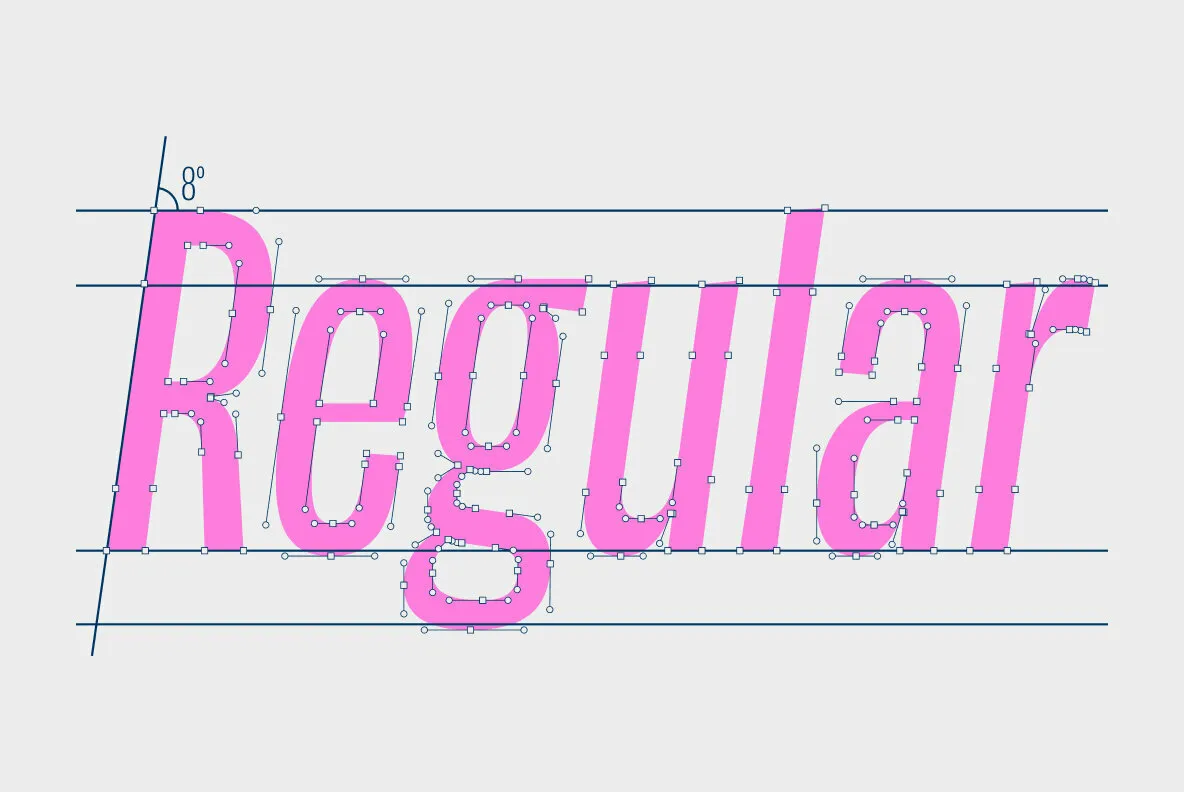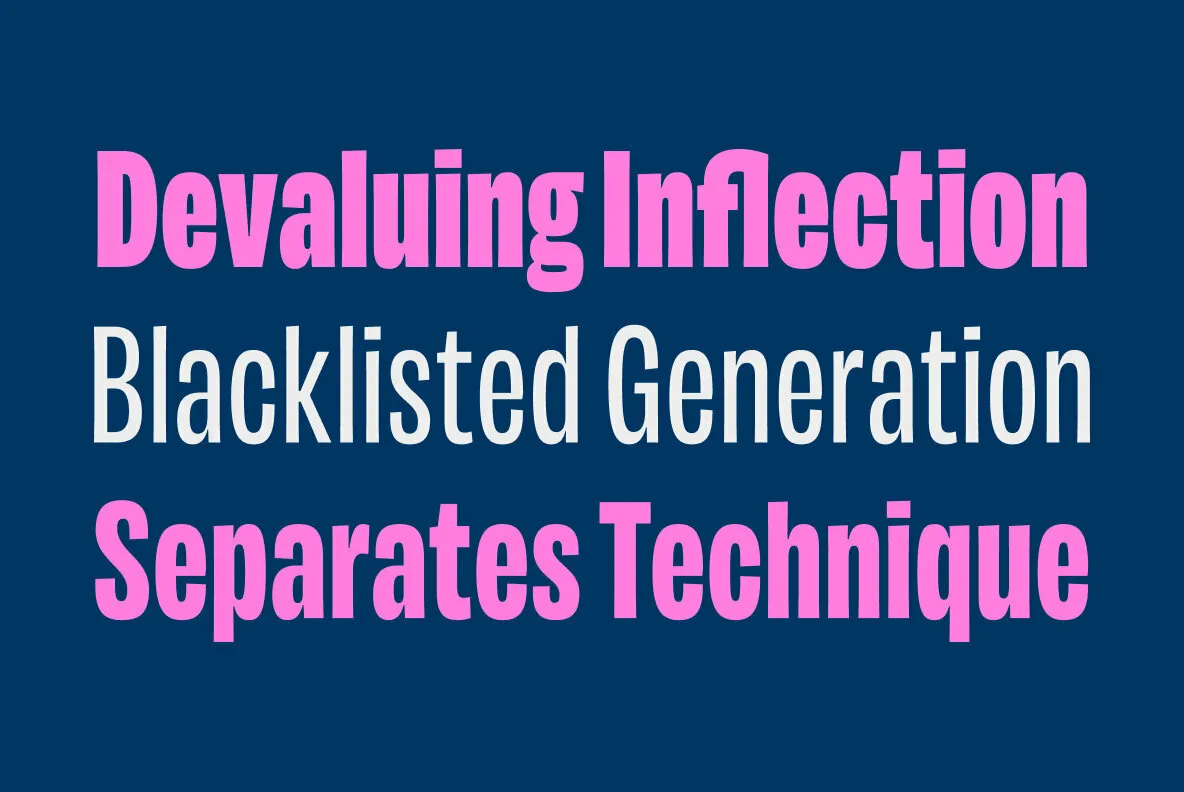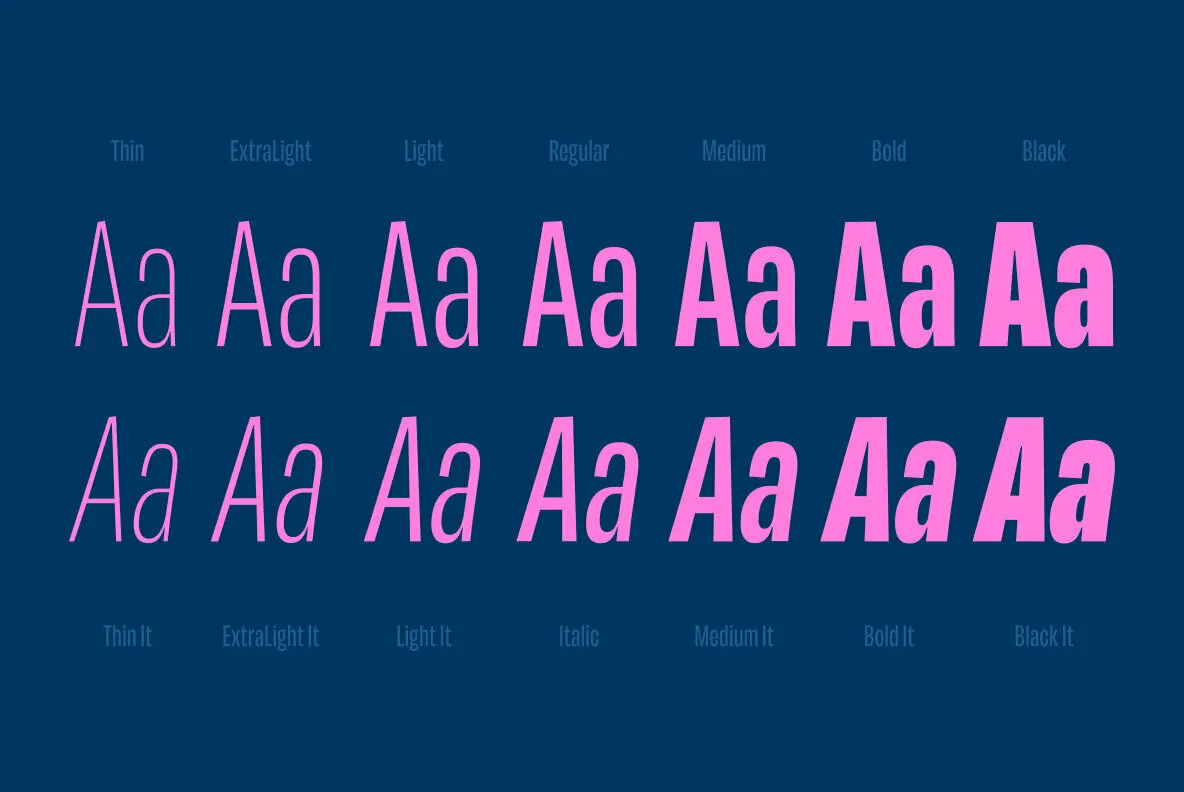
Maleo Font Family
Description de Maleo Font Family
Maleo est un sans d’affichage contemporain aux racines grotesques, s’inspirant de polices de caractères telles que Franklin Gothic et Alternate Gothic de Benton et de polices contemporaines telles que évidemment et Mars Condensed.
Conçue par Aditya Wiraatmaja comme sa première police de caractères pour le commerce de détail, Maleo est principalement conçue pour une utilisation de grande taille. Son petit terminal évasé et coupé en angle lui confère une présence conviviale et accessible. Avec une famille de 14 styles allant du fin au noir avec des italiques assortis, il s’agit d’un type d’affichage polyvalent qui se démarque dans les gros titres, tout en dégageant une personnalité charmante.
Maleo prend en charge plusieurs langues et est équipé de nombreuses fonctionnalités OpenType, notamment : Figures de style ancien, ligature, fractions, numérateurs et dénominateurs et variantes stylistiques.